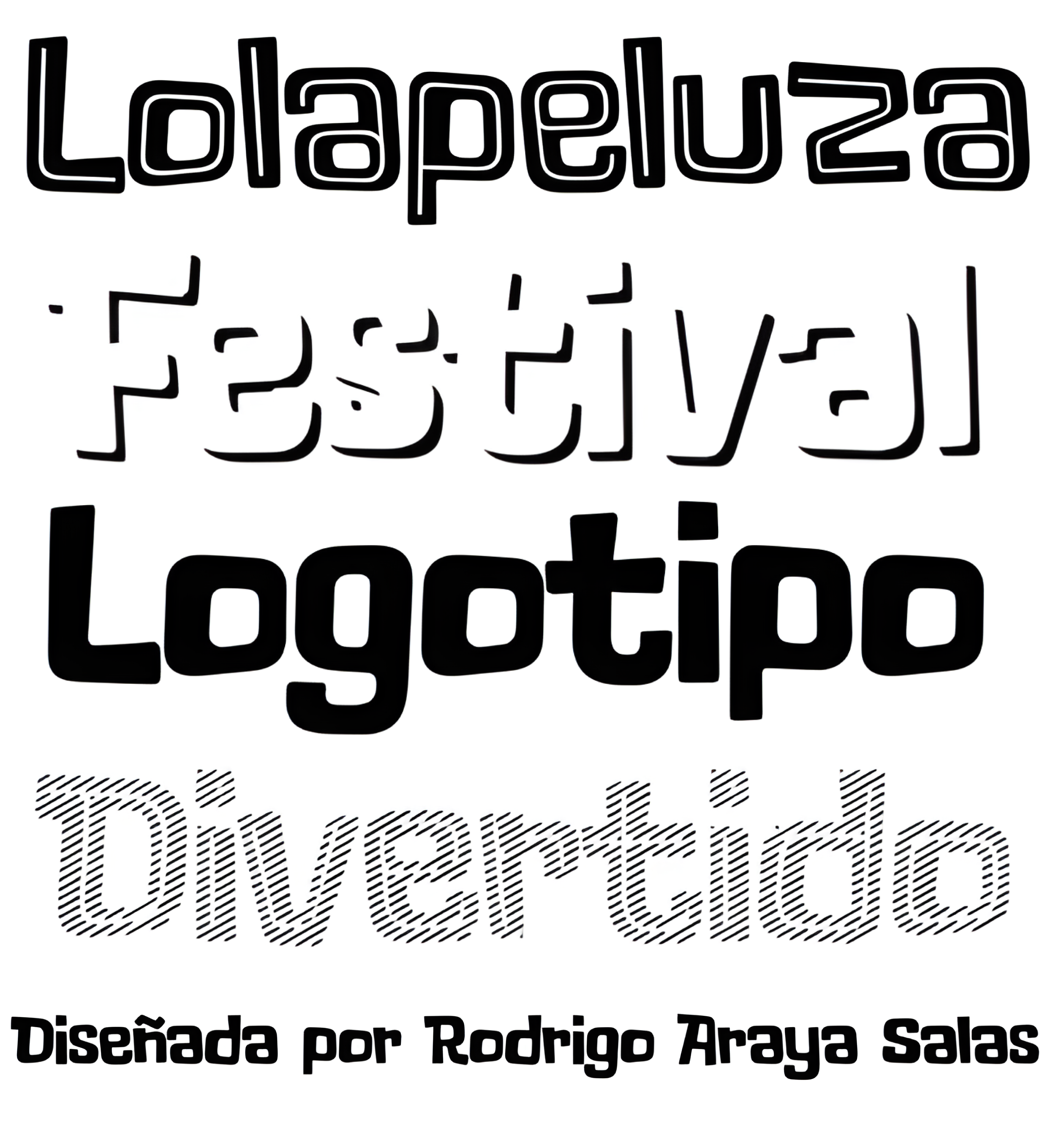
| Créditos | Rodrigo Araya Salas, Héctor Barroso |
| Descripción | Inspirado en el logotipo de «Lollapalooza». La intención era diseñar un tipo de letra alegre y divertido. Lolapeluza funciona perfectamente para diseños infantiles y juveniles. También se incluyen 4 variantes: -Regular: Conjunto básico -Negro: Línea pesada. Lolapeluza puede correr por encima o por detrás de un texto -Sombra. También se incluye un alfabeto cirílico para mejorar, pero la tipografía es más un conjunto de alternativas. |
| Familia(s) | Lolapeluza, Lolapeluza Black, Lolapeluza Shadow, Lolapeluza Line |
| Estilos | 4 |
| Fundidora | RodrigoTypo |